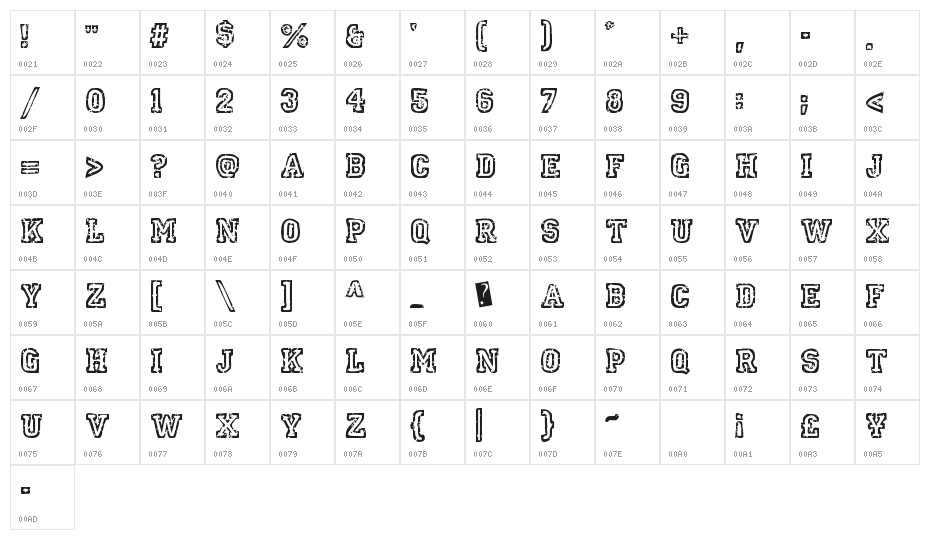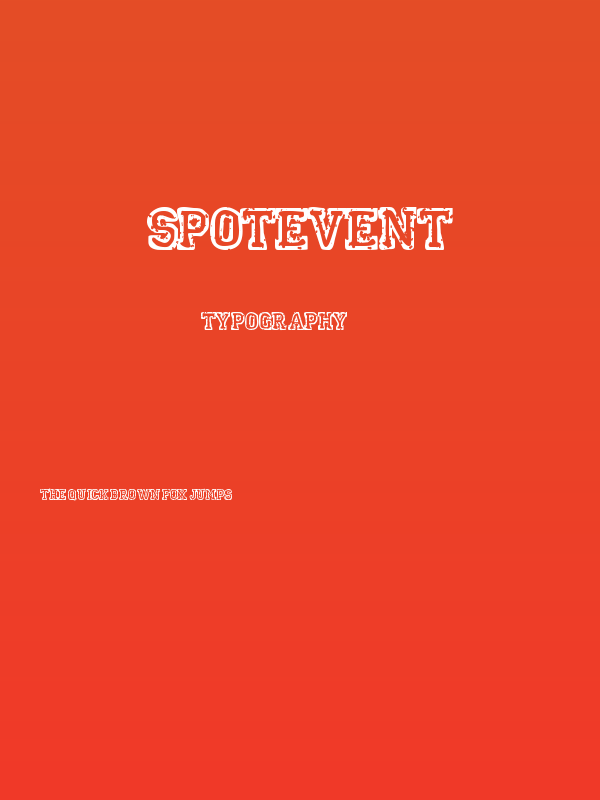
SpotEvent Font
| Progetti proposti | Ideal for poster designs, album covers, branding for edgy or alternative products, and any project seeking a vintage or distressed look. |